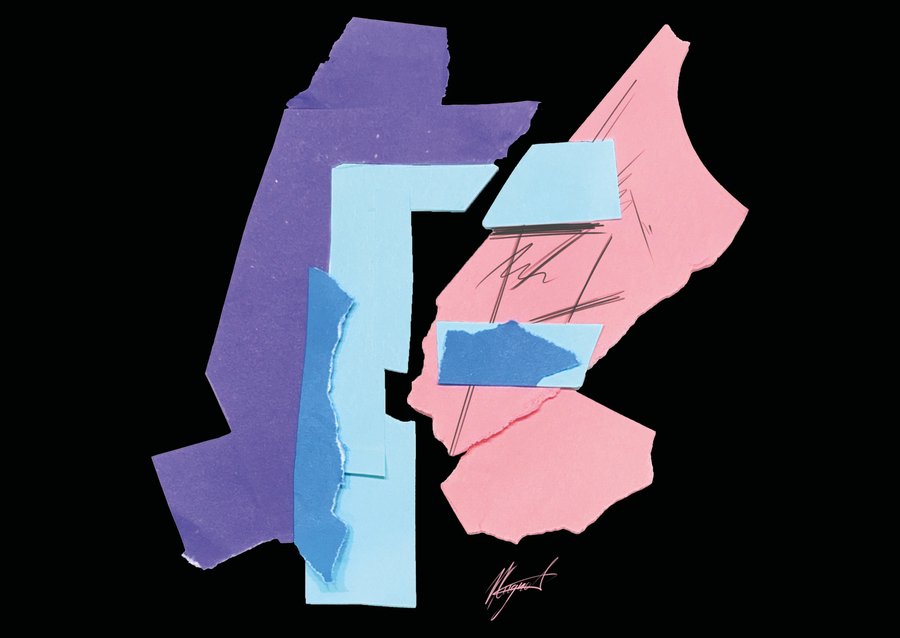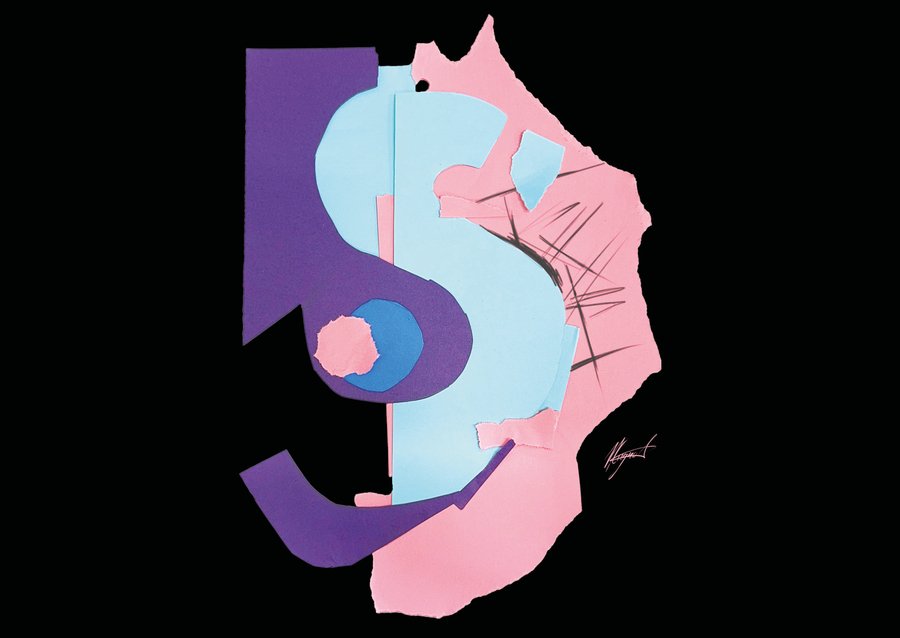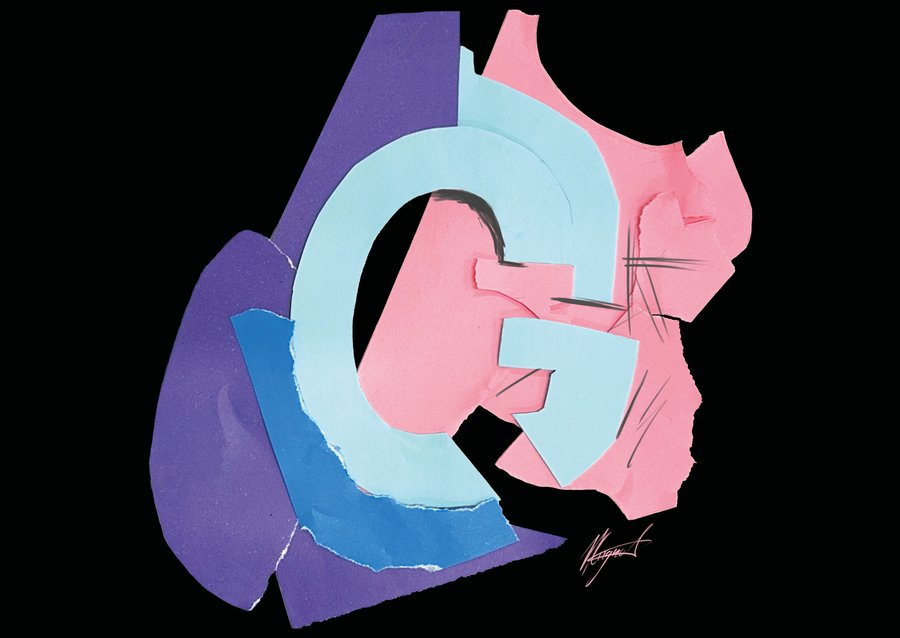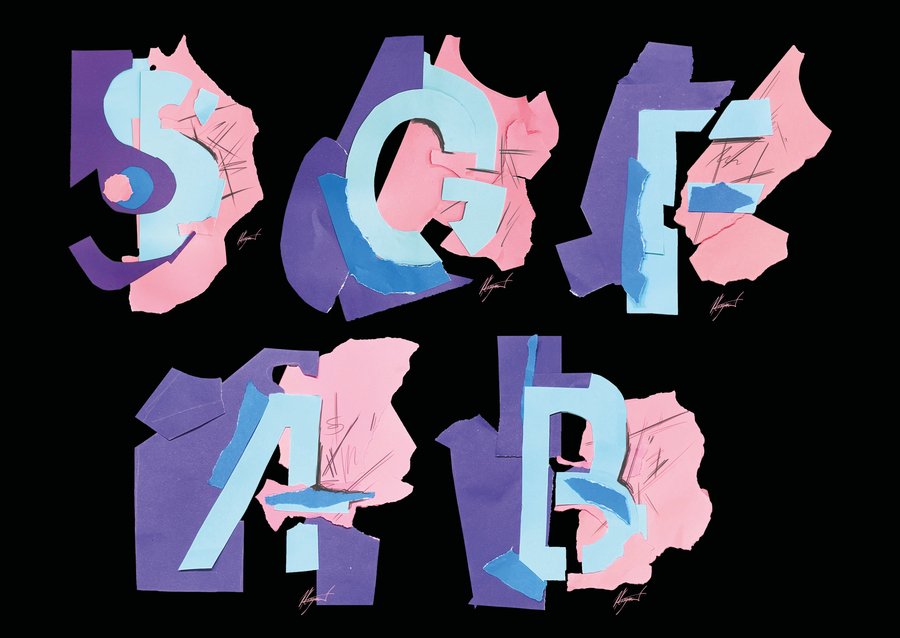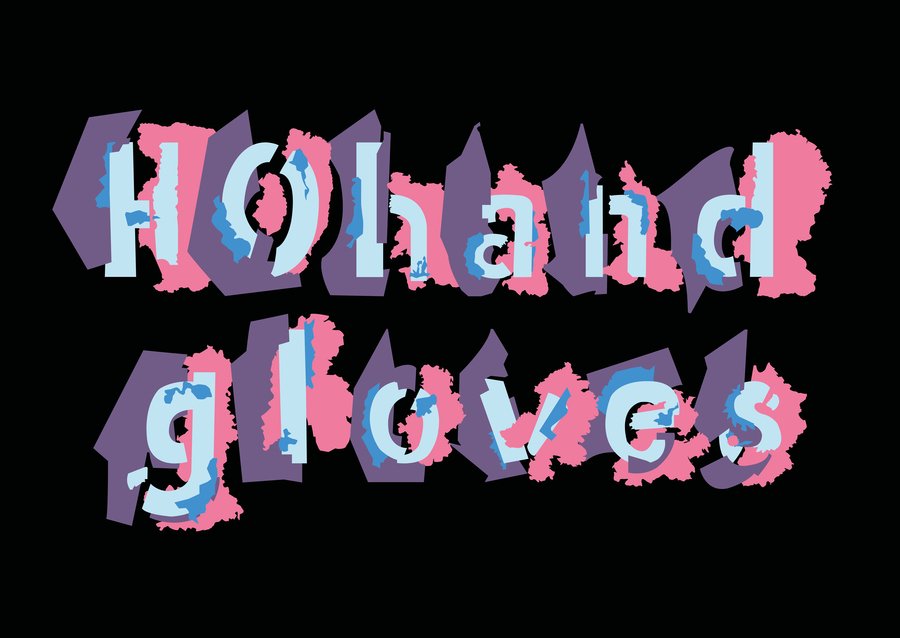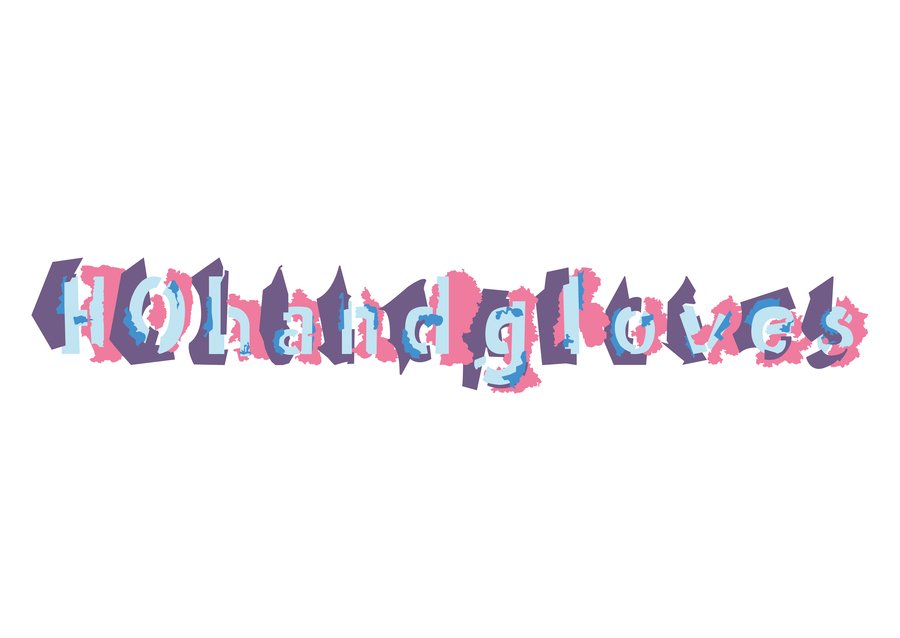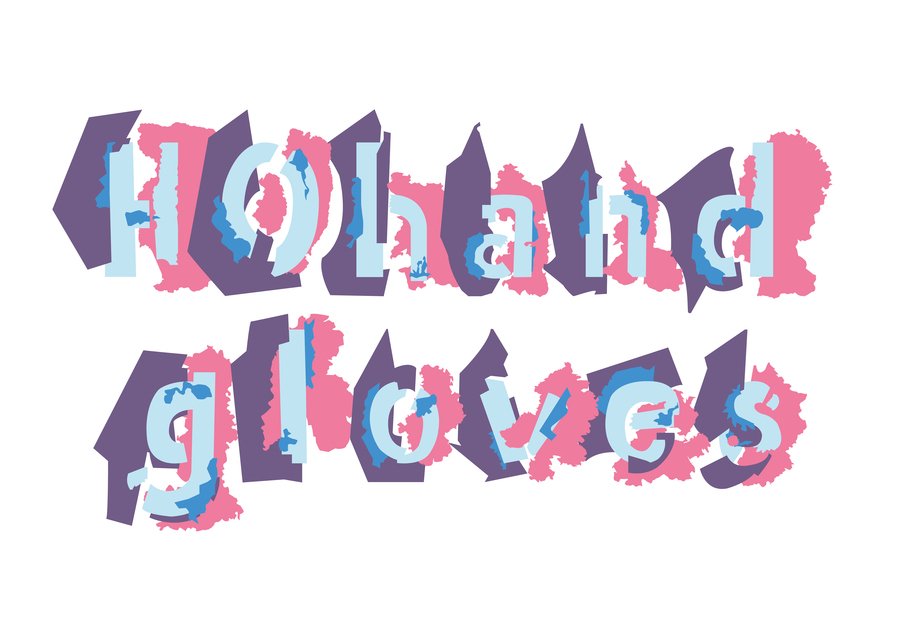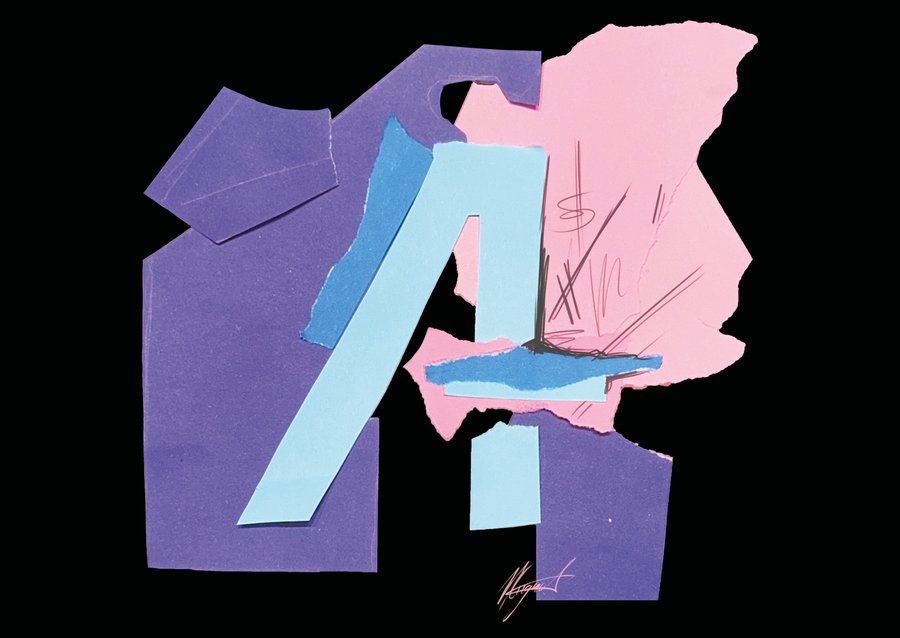
Saturate[d] font
Серия эскизов для Saturate[d] font, яркого четырехцветного шрифта, который можно реализовать как на плоскости, так и в объеме
коллажи: контрформа, контррельеф, плоскость, линия, полутон